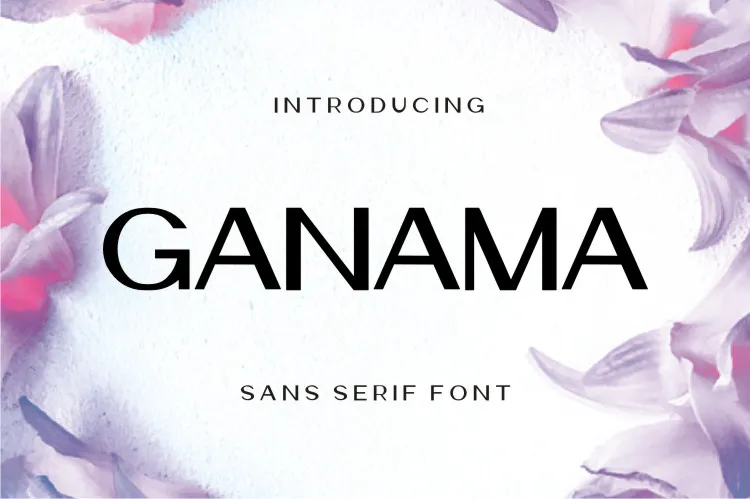
A fonte ‘Ganama Font’ é uma escolha ideal para designers que buscam elegância contemporânea sem perder a simplicidade. Desenvolvida pela equipe do letterfiastudio, essa fonte sans serif tem um aspecto fresco e moderno. Ela se destaca por seu formato alto e simples, o que a torna perfeita para criar designs em variedades de materiais e ambientes. Seja para uma camiseta desportiva, um logotipo ou até mesmo anúncios de moda, ‘Ganama Font’ oferece uma solução clara e moderna. Esta font é amplamente versátil, adaptando-se com sucesso a várias aplicações gráficas, permitindo que os designers criem designs frescos e atuais. Com ‘Ganama Font’, você pode transformar seus projetos em um verdadeiro destaque no mundo da design.